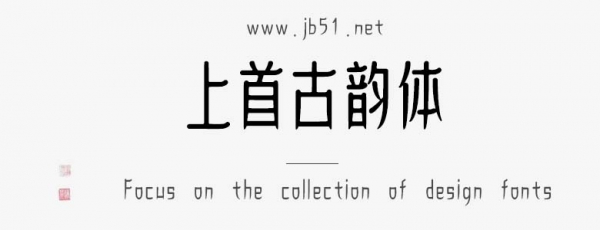
上首古韻體是由上首造字字庫(kù)出品的字體,字體筆觸略細(xì),字形端正,具有很好的視覺感,適合應(yīng)用于藝術(shù)設(shè)計(jì)、平面宣傳設(shè)計(jì)、網(wǎng)頁(yè)設(shè)計(jì),書法字帖等領(lǐng)域,需要的朋友可以前來(lái)本站下載。